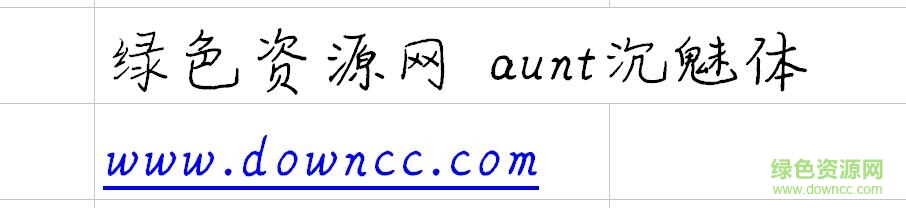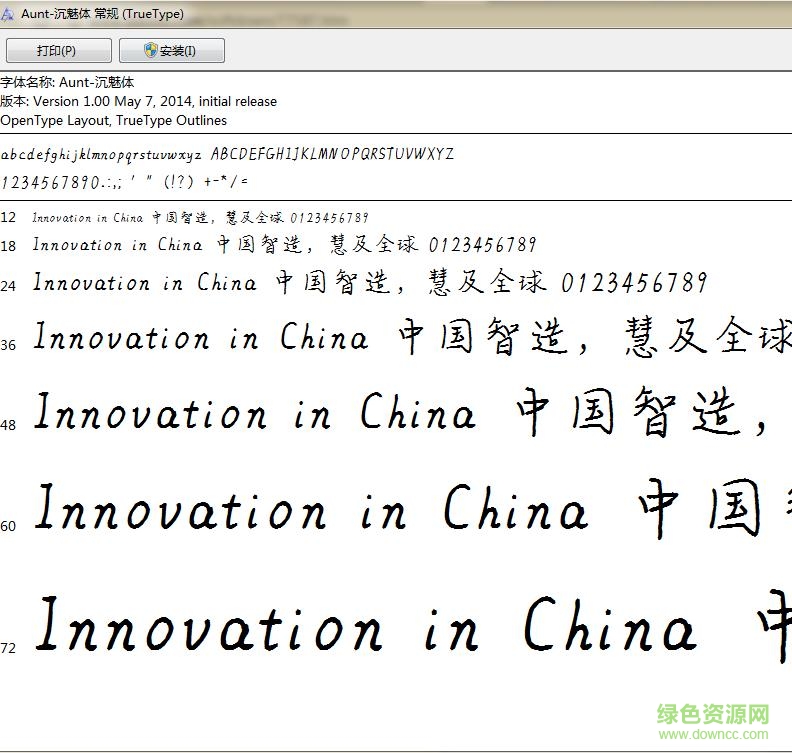
沉魅體ttf擁有一股十分濃厚的古風(fēng)韻味,字里行間透露出優(yōu)雅的風(fēng)格,讓你在使用這款字體的時(shí)候能夠感受到部分不錯(cuò)的精神享受,每一個(gè)字體的形式仿若沉睡不已的樣子,快來綠色資源網(wǎng)下載吧!
在眾多的字體風(fēng)格中這款字體還是比較不錯(cuò)的,能夠讓你在各類制作以及寫作過程中獲得獨(dú)家享受,在文字輸入聊天的時(shí)候也能夠帶給你好友不錯(cuò)的閱讀效果!
1、沉魅體線條勻稱無論點(diǎn)畫長短。筆畫均呈粗細(xì)劃一的狀態(tài)
2、沉魅體運(yùn)用途徑十分廣泛,能夠運(yùn)用到印刷行業(yè)讓你打印出不錯(cuò)的文字
3、這款字體還能運(yùn)用到電子制作上實(shí)現(xiàn)藝術(shù)字顯示效果